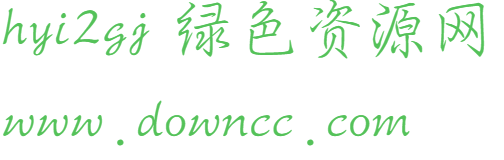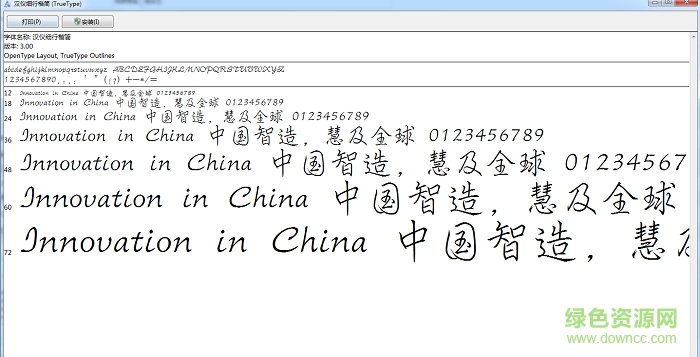
hyi2gj(漢儀細(xì)行楷)
hyi2gj是什么字體?hyi2gj字體就是漢儀細(xì)行楷字體,這款字體比起楷體更張揚(yáng)瀟灑,線條靈活多樣,行筆巧妙,漂亮好看,喜歡這款字體的朋友快來(lái)下載收藏吧!
行楷字體介紹
行楷,也稱“漢字行楷手寫體字形”,是偏重于楷書書寫筆法(法則),比楷書行筆自由,又比行草規(guī)正的行書字體?;蛟唬菏菨h字在楷書基礎(chǔ)上簡(jiǎn)約書寫筆畫、增強(qiáng)書寫映帶。
hyi2gj字體
行楷字體特點(diǎn)
1.行楷的筆順不是一成不變的。行楷的書寫,根據(jù)實(shí)際需要,個(gè)別地方由于書寫到具體部位時(shí),筆畫的連結(jié)、縈帶、減省等使字形變化,相應(yīng)的筆順也隨之改變了。
2.行楷結(jié)字也很自由,字的筆畫可依據(jù)不同連筆位置的需要作出靈活多樣的變化,書寫快捷,不需停筆、頓筆更長(zhǎng)的時(shí)間。下筆收筆,起承轉(zhuǎn)合,多取順勢(shì),一筆帶過(guò)。
3.寫行楷的過(guò)程中,個(gè)別時(shí)候由于連帶的需要,加上個(gè)別筆畫的合并、替代和減省,很多筆畫自然地連在一起書寫,筆數(shù)會(huì)比楷書有所減少。